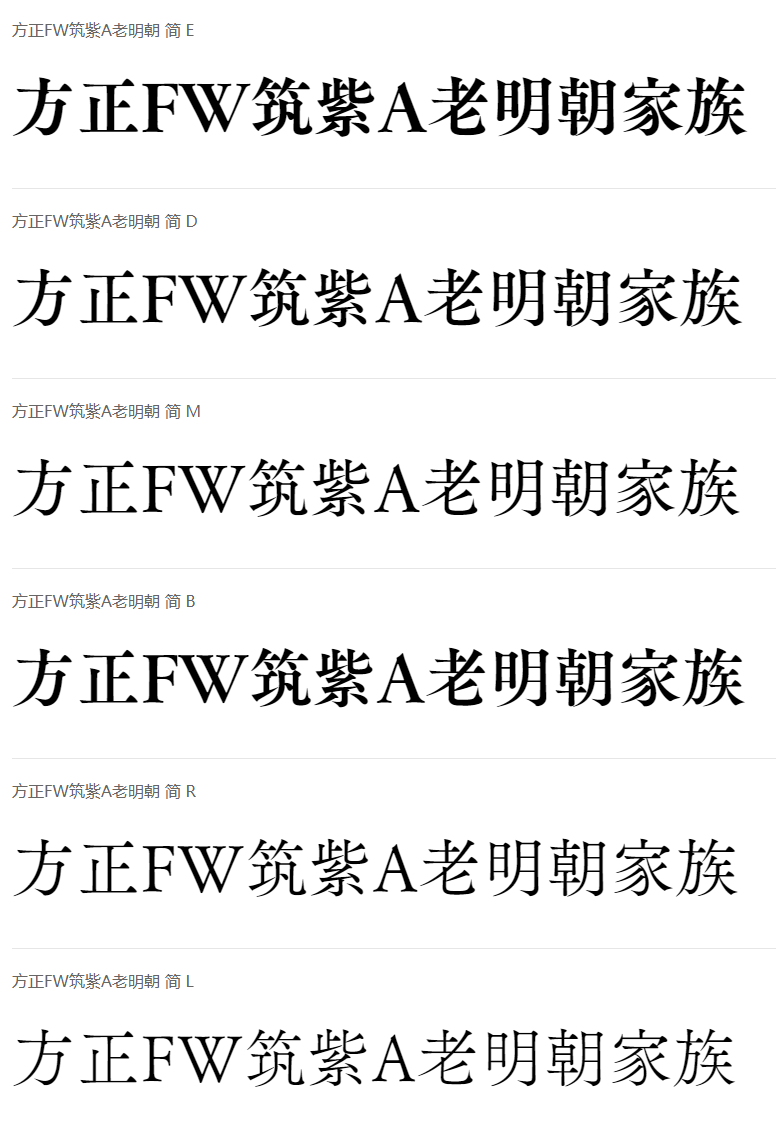
方正FW筑紫A老明朝家族
是“筑紫字体”的旧式风格的宋体。特点是漂亮地投入,轻松地弹起、伸展。对2008年发布的筑紫旧式宋体的部分“汉字”进一步进行了舒展设计,对字体名称重新汇集了六个字重的家族字。狭窄空间的设计,文字不是图形式的,看上去的确是文字。是一种似乎是将文本排列起来的瞬间发出声音的书法风格。字母数字采用Garamond系列的设计,展现出富有表现力和令人玩味的“汉字”和“假名”的书法风格。
「筑紫書体」のオールドスタイルの明朝体です。美しい打ち込みや伸びやかなハネ、ハライが特徴的な書体です。2008年にリリースした筑紫オールド明朝の一部の「漢字」のデザインをさらに伸びやかにリデザインし、書体名も新たに6ウエイトのファミリーを揃えました。狭いふところのデザインは、文字が図形的ではなく文字らしく見えてきます。テキストを組んだ瞬間に音を発するような書風です。英数字はガラモン系のデザインを採用することで、表情豊かで味わい深い「漢字」「かな」の書風が生きてきます。